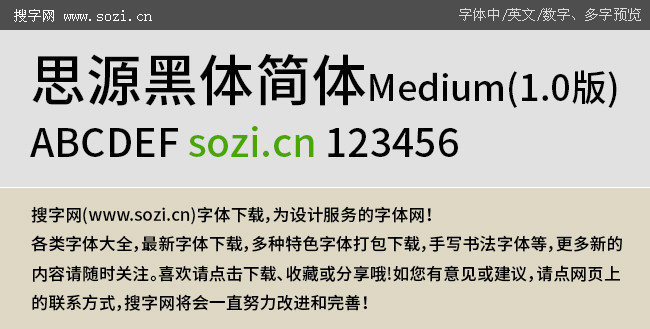
思源黑體簡(jiǎn)體Medium1.0
搜字網(wǎng)提供一款思源黑體簡(jiǎn)體Medium1.0中文字體下載,思源黑體是一款由谷歌聯(lián)合Adobe發(fā)布全新開(kāi)源字體,是一款免費(fèi)、開(kāi)源黑體字體。可共同呈現(xiàn)一致的視覺(jué)美感。本作品適用于書(shū)籍排版、報(bào)紙排版、畫(huà)冊(cè)設(shè)計(jì),網(wǎng)頁(yè)設(shè)計(jì)等應(yīng)用。